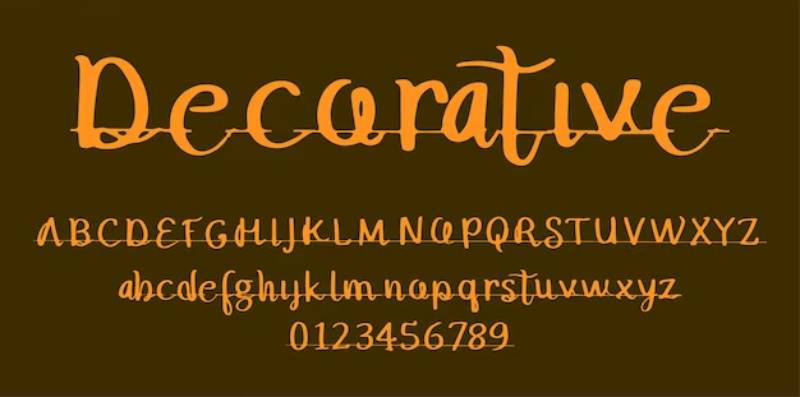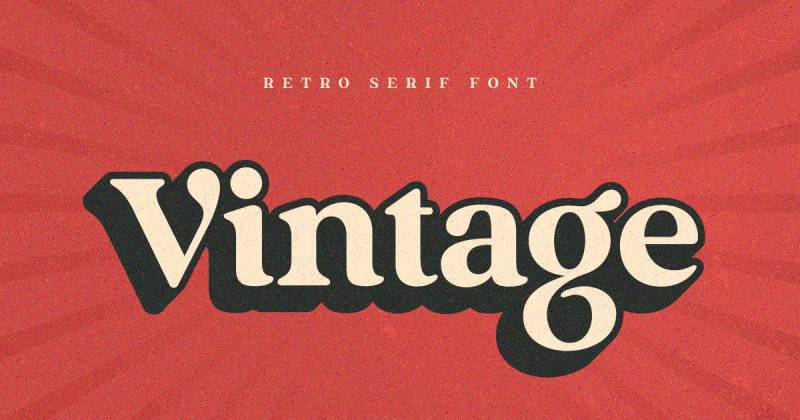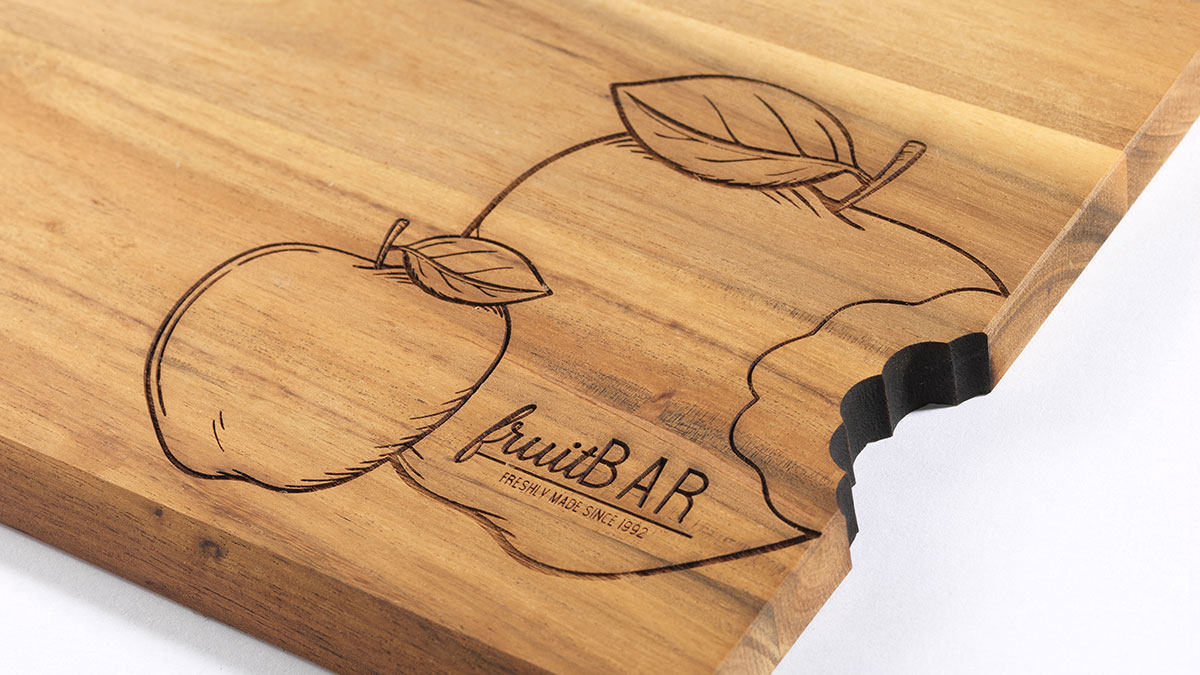
Haben Sie sich jemals über die Präzision eines lasergeschnittenen Designs gewundert?
Es gibt eine Kunst darin, eine Typografie auszuwählen, die nicht nur Ihre Botschaft vermittelt, sondern auch den Kuss des Lasers übersteht.
Es geht nicht nur um Ästhetik; die besten Schriftarten für das Laserschneiden überschreiten den digitalen Raum und treten klar und deutlich aus dem glühenden Pfad des Strahls hervor.
Wenn Sie in dieses Handwerk eintauchen, werden Sie feststellen, dass die Auswahl der Schriftart Ihr Projekt machen oder brechen kann.
In diesem Artikel werden Sie die subtilen Feinheiten von lasergravierten Schriftarten und Schriftlesbarkeit auf Materialien erkunden.
Wir werden untersuchen, wie Vektorschriften und spezifische Designsoftware harmonieren, um herausragende Ergebnisse zu erzielen. Ob Sie schickes Acryl oder robustes Sperrholz gravieren, die richtigen typografischen Begriffe sind wichtig.
Erwarten Sie, dass Sie mit einem Toolkit voller Wissen über schnittfreundliches Schriftdesign davonkommen.
Von Schablonenschriften bis hin zu fett lesbaren Schriftarten wird Ihre Schriftpalette zehnfach erweitert. Tauchen Sie tief in das Reich ein, in dem Schriftart und Laser aufeinandertreffen, und heben Sie Ihre Designs von gut auf bemerkenswert.
Die besten Schriftarten für das Laserschneiden
| Schriftart | Typ | Lesbarkeit | Geeignet zum Schneiden | Anmerkungen |
|---|---|---|---|---|
| Arial | Serifenlos | Hoch | Sehr geeignet | Klar, unkompliziert, ohne komplizierte Details |
| Arial Black | Serifenlos | Hoch | Sehr geeignet | Fett gedruckte Version von Arial, klar für das Schneiden |
| Verdana | Serifenlos | Hoch | Sehr geeignet | Breiter Abstand, gut für größere Schnitte |
| Helvetica | Serifenlos | Hoch | Geeignet | Klassisch und weit verbreitet, jedoch nicht so verfügbar für nicht-kommerzielle Nutzung aufgrund von Lizenzierung |
| Impact | Serifenlos | Hoch | Sehr geeignet | Dicke Striche, gut für kühne Aussagen |
| Futura | Geometrisch serifenlos | Hoch | Geeignet | Geometrische Formen, klar und modern |
| Schablone | Serifenlos | Mittel | Geeignet | Entworfen mit Unterbrechungen wie Schablonen, kann bei kleinen Schnitten knifflig sein |
| Times New Roman | Serif | Mittel | Weniger geeignet | Serifen können bei kleineren Größen problematisch sein |
| Bree Serif | Mittel | Weniger geeignet | Serifen können möglicherweise nicht sauber geschnitten werden |
Serifenschriften
Stellen Sie sich die Klassiker vor, wie Times New Roman oder Bree Serif. Serifenschriften haben diese kleinen Füße, bekannt als Serifen, an jedem Buchstabenende.
Sie bringen eine traditionelle Atmosphäre, irgendwie wie dieser altmodische Charme. Diese Schriftarten mit ihren kleinen Linien und eleganten Abschlüssen sind perfekt für Projekte, die einen Hauch von Eleganz benötigen.
Aber hier ist der Haken: Beim Laserschneiden können diese kleinen Serifen ein wenig knifflig sein, besonders bei Materialien wie Holz, wo Präzision entscheidend ist. Daher sollten Sie das Material und die Fähigkeiten des Lasers berücksichtigen.
Serifenlose Schriftarten
Jetzt lernen Sie die sauber geschnittenen, modernen Schriftarten kennen: Arial, Verdana, Helvetica. Serifenlose Schriften verzichten auf die Füße für ein schlankes, linienbasiertes Aussehen.
Sie sind wie die Minimalisten unter den Schriftarten – ohne Schnickschnack, nur gerade Linien. Perfekt für ein zeitgenössisches Design, oder?
Und raten Sie mal, sie sind ein Traum beim Laserschneiden. Ihre Klarheit und Einfachheit bedeuten, dass sie großartig für fast jedes Material sind, besonders wenn Sie Lesbarkeit und Deutlichkeit benötigen.
Skript- und Handschrift-Schriften
Machen wir es schick mit Schreibschriften und Handschrift-Schriften. Denken Sie an Great Vibes, Dancing Script, Autery. Sie sind wie die Schreibschrift, die man in der Schule gelernt hat, nur viel cooler. Diese Schriftarten ahmen handgeschriebenen Text nach und haben oft verbundene Buchstaben.
Stellen Sie sie sich auf einer schicken Einladung oder einem personalisierten Geschenk vor – sie fügen eine elegante, persönliche Note hinzu. Aber, nur zur Warnung: Ihr aufwendiges und fließendes Design kann beim Laserschneiden eine Herausforderung darstellen, besonders wenn das Design sehr detailliert ist oder das Material weniger nachgiebig ist.
Display-Schriften
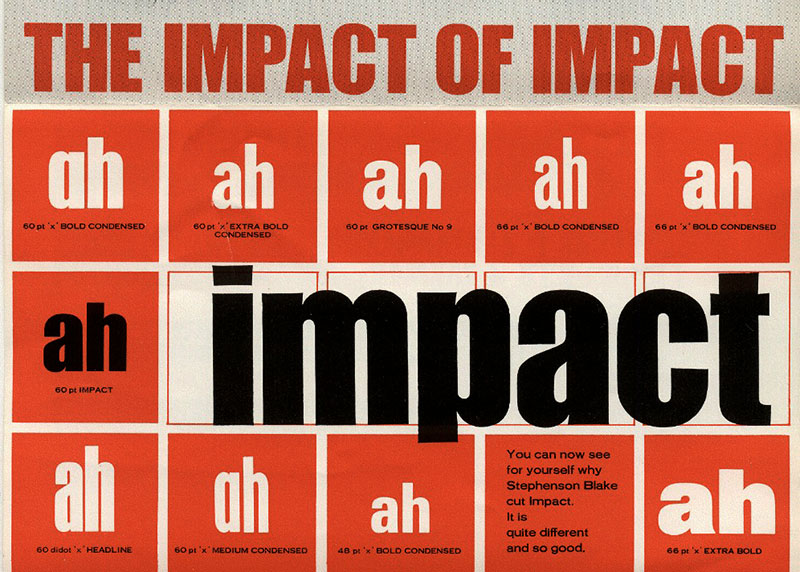
Zu guter Letzt, die Showstopper: Display-Schriften. Impact, Schablone, Bistern – diese Schriftarten sind dafür gemacht, eine Aussage zu treffen.
Sie sind fett, sie sind dekorativ, und sie sind dafür gemacht, im Rampenlicht zu stehen – denken Sie an Überschriften oder Beschilderungen. Sie funktionieren wunderbar beim Laserschneiden, wenn Sie möchten, dass Ihre Botschaft nicht nur geflüstert, sondern gerufen wird.
Aber denken Sie daran, mit großer Kraft kommt große Verantwortung: ihre kühne Natur bedeutet, dass Sie das Material und die Schnittpräzision berücksichtigen müssen.